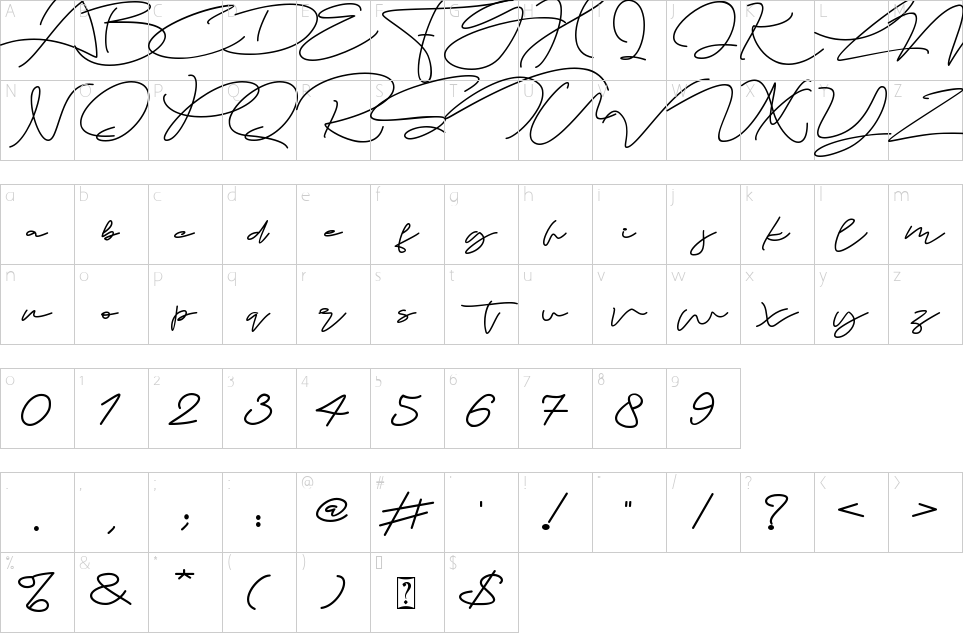
A fonte ‘Margareta’ é uma elegante opção para aqueles que buscam um equilíbrio entre simplicidade e elegância. Desenvolvida por Thomas Aradea, ela traz um ar de sofisticação sem ser excessivamente elaborada. Com uma grade de caracteres clara e uma tipografia fluida, Margareta é perfeita para aplicações que valorizam a perfeição na leitura e no design. Sujeitando-se ao uso em ambientes Windows e Mac, Margareta tem se destacado como uma opção de fonte ideal para designers gráficos. Sua simplicidade permite que você enfatize o conteúdo da sua peça de design sem comprometer a legibilidade. O fato de que ela foi baixada 424 vezes é uma indicação clara de seu valor e popularidade entre os criadores de design. Margareta é uma fonte que traz ao design uma qualidade que se equilibra perfeitamente entre a praticidade e o encanto, tornando-se uma fonte de escolha para criadores que buscam uma solução de fonte moderna e de alto nível.